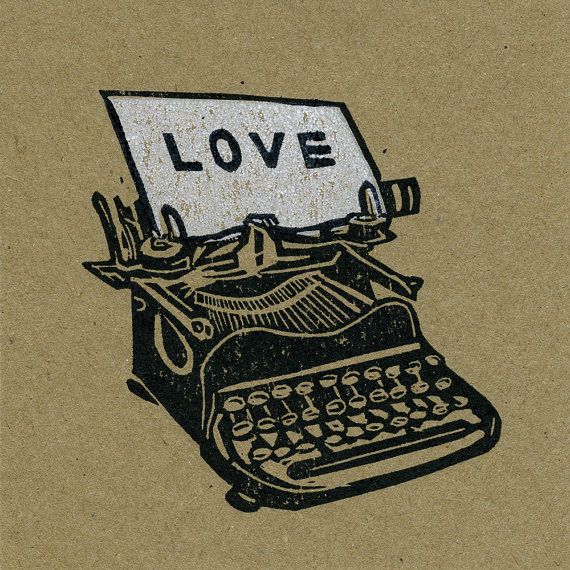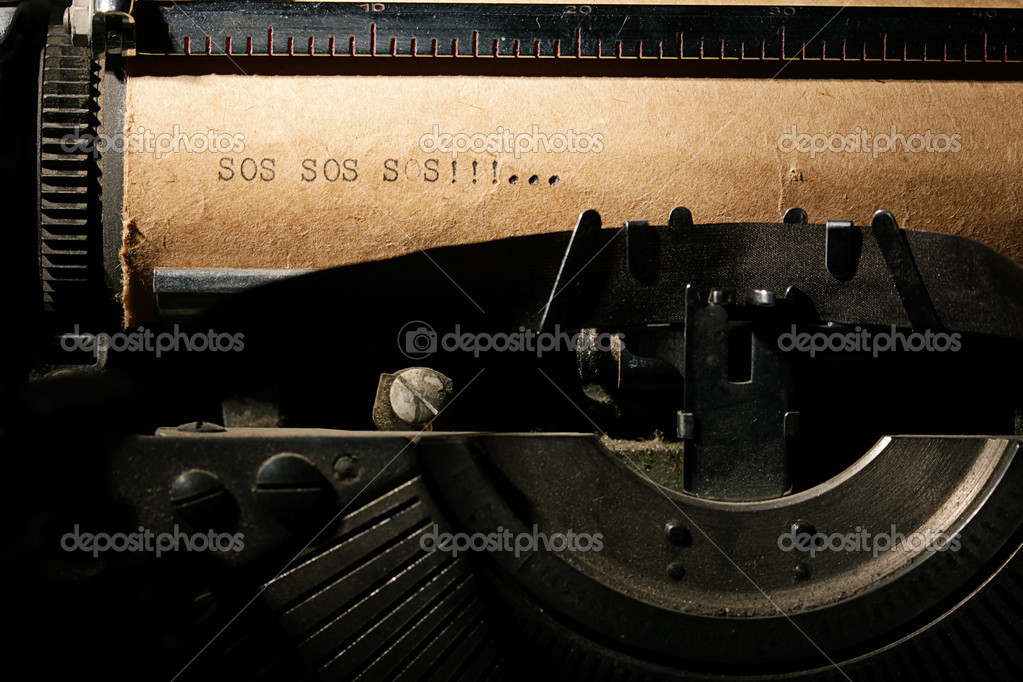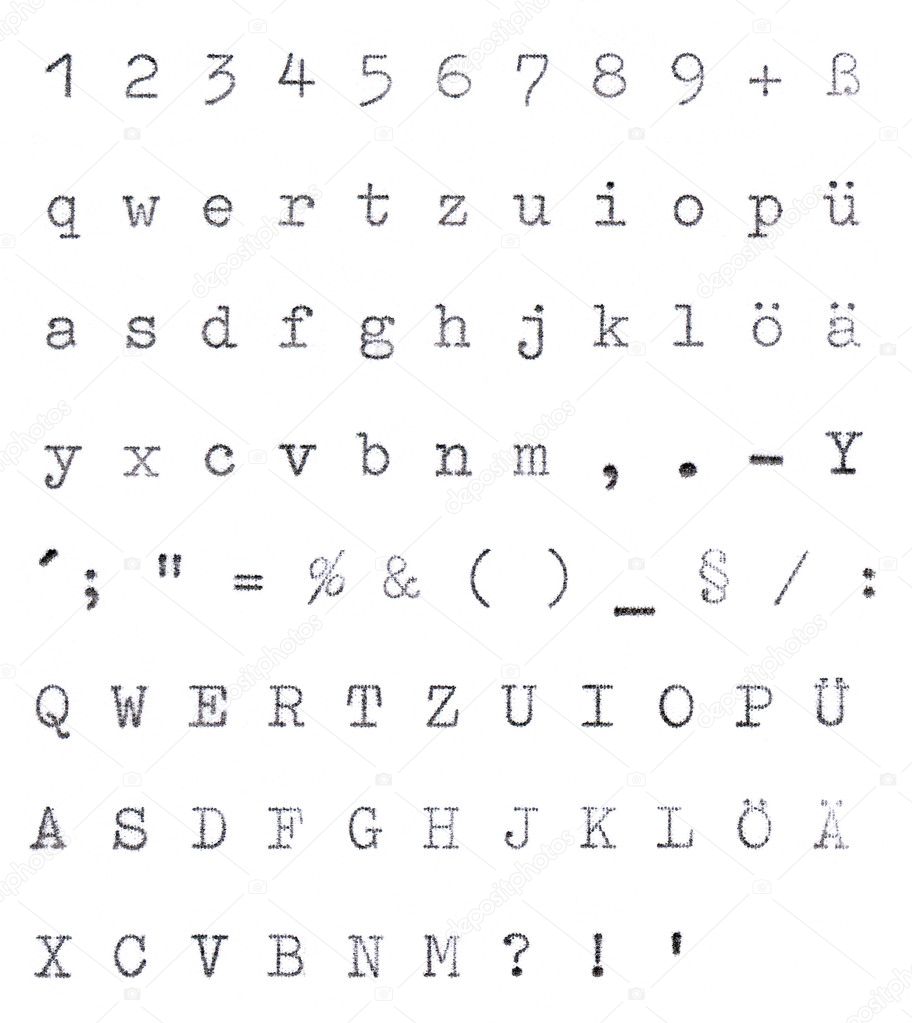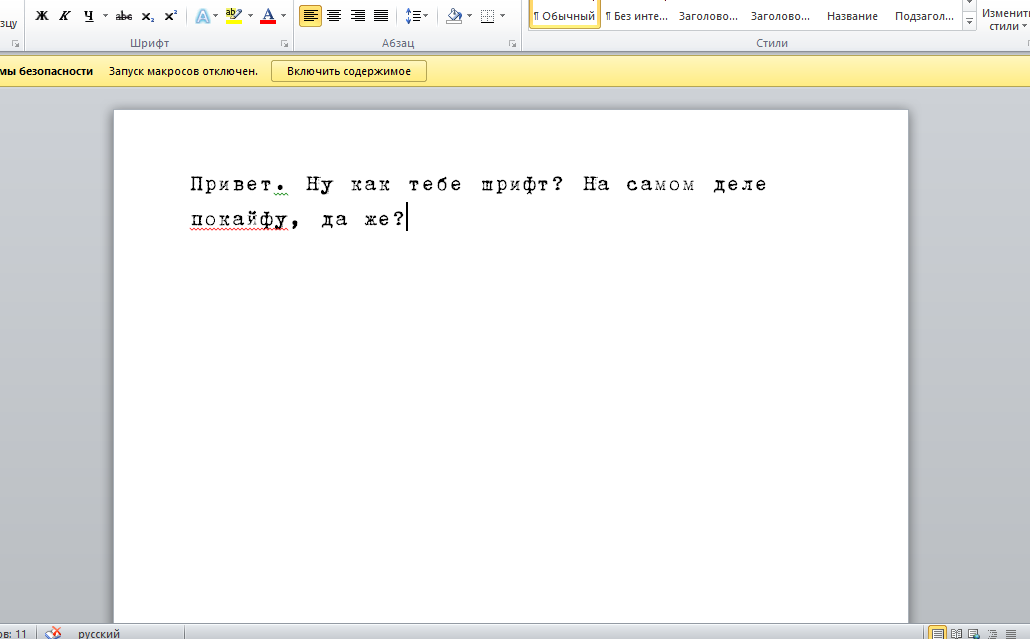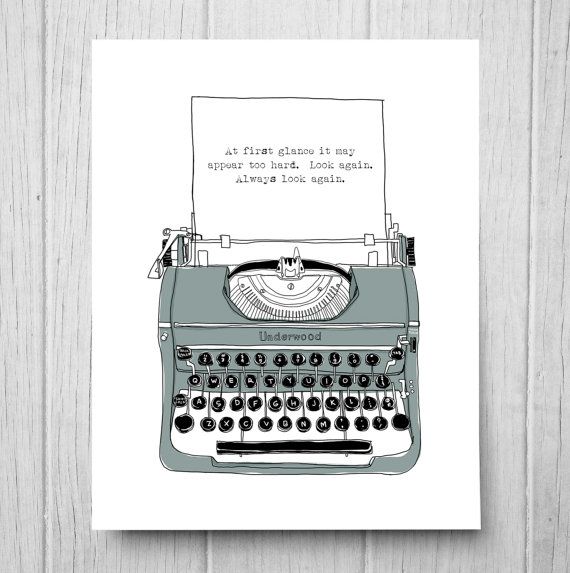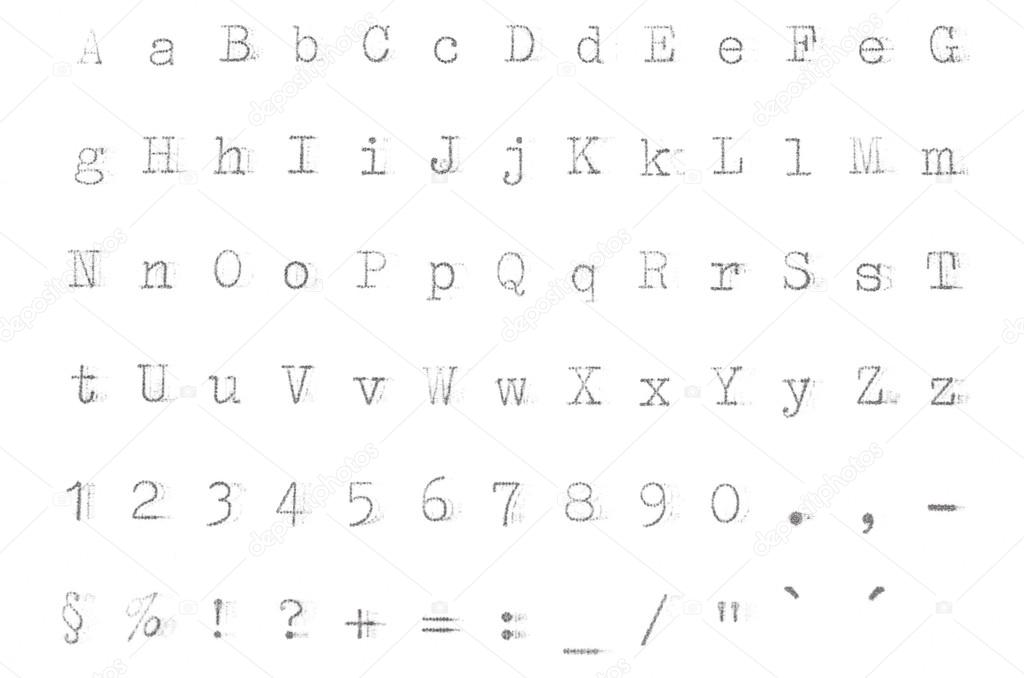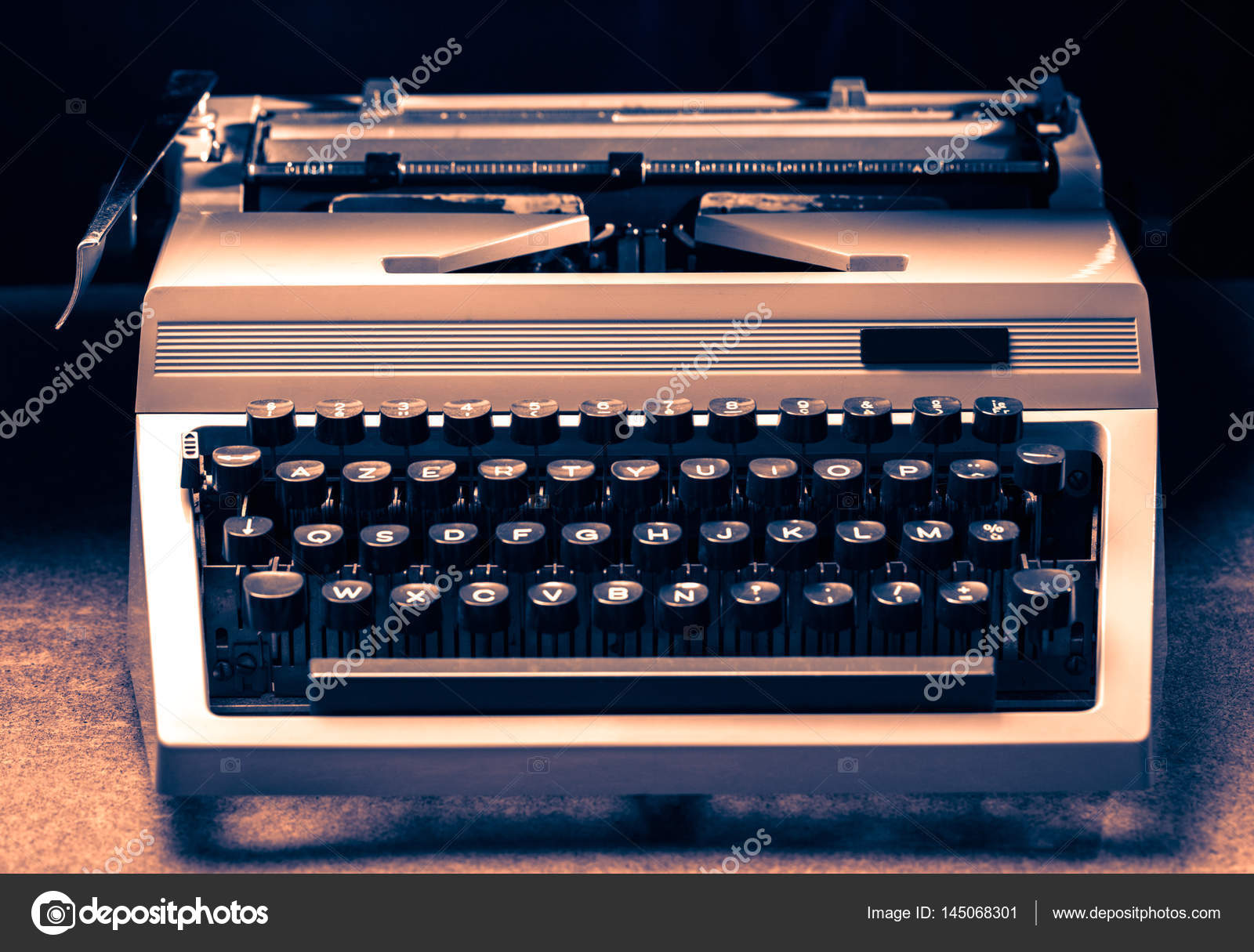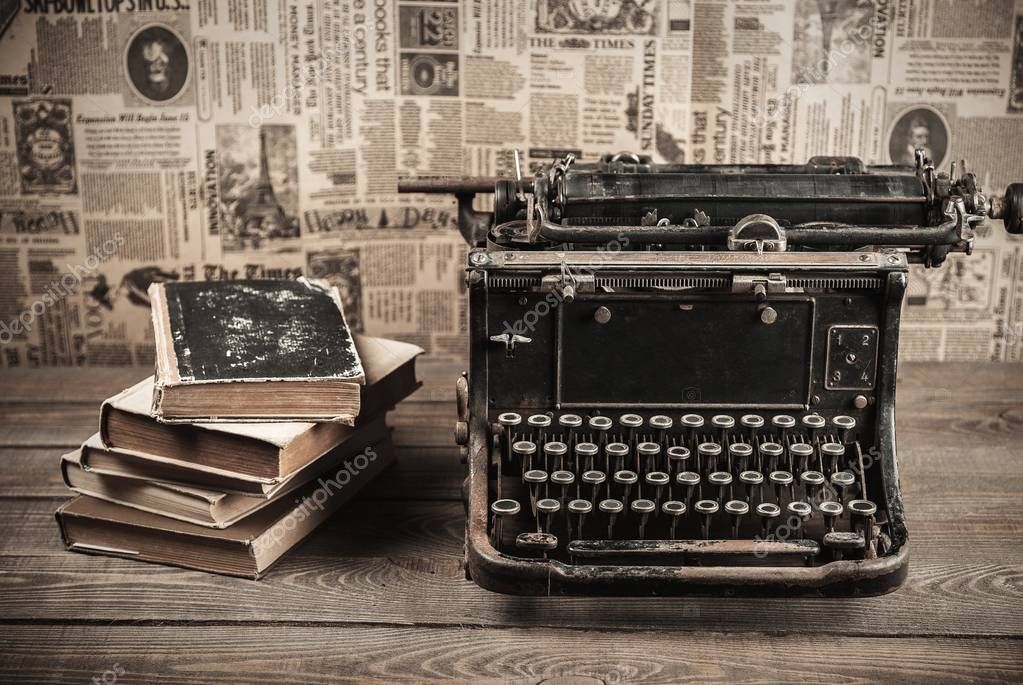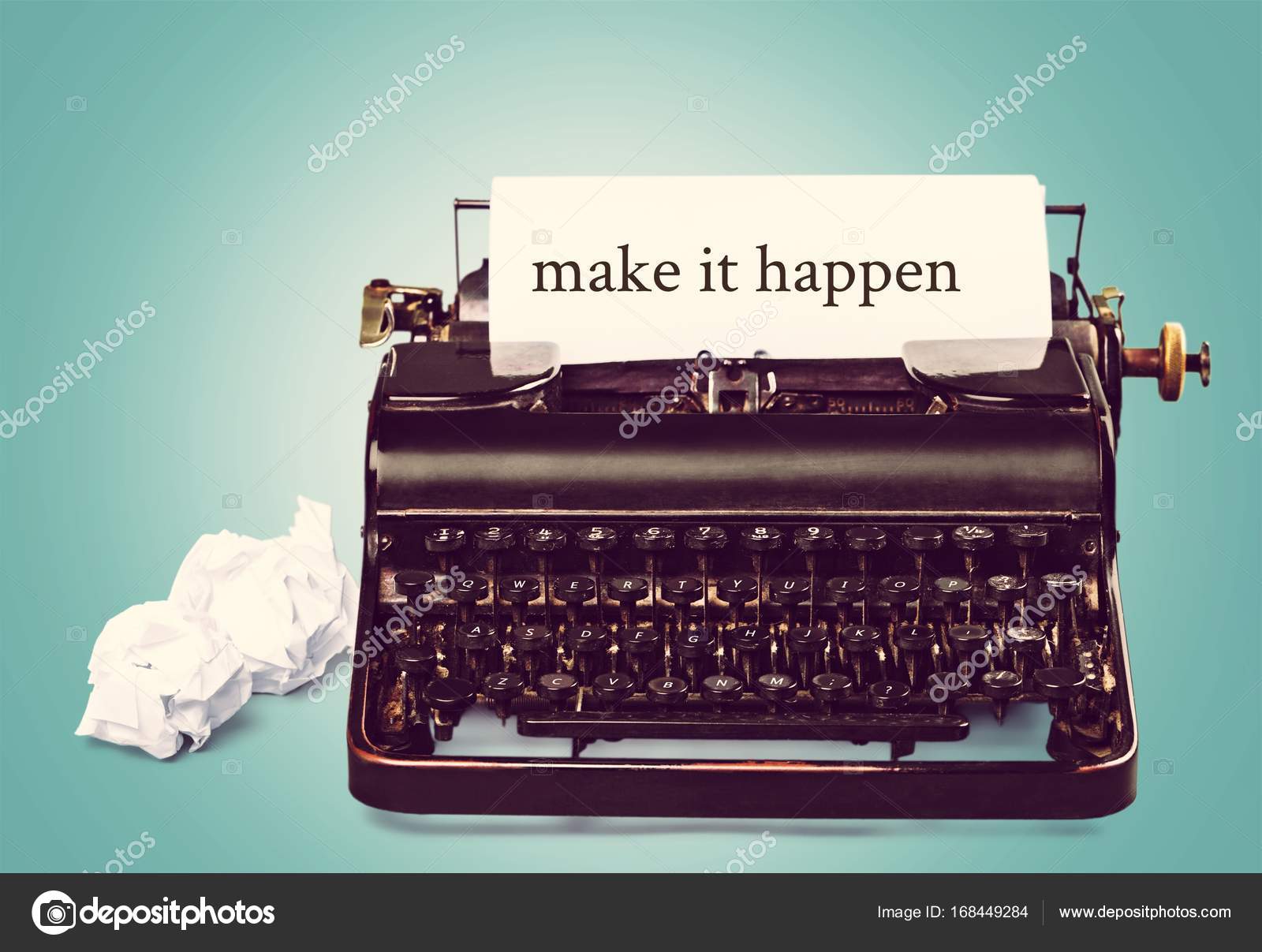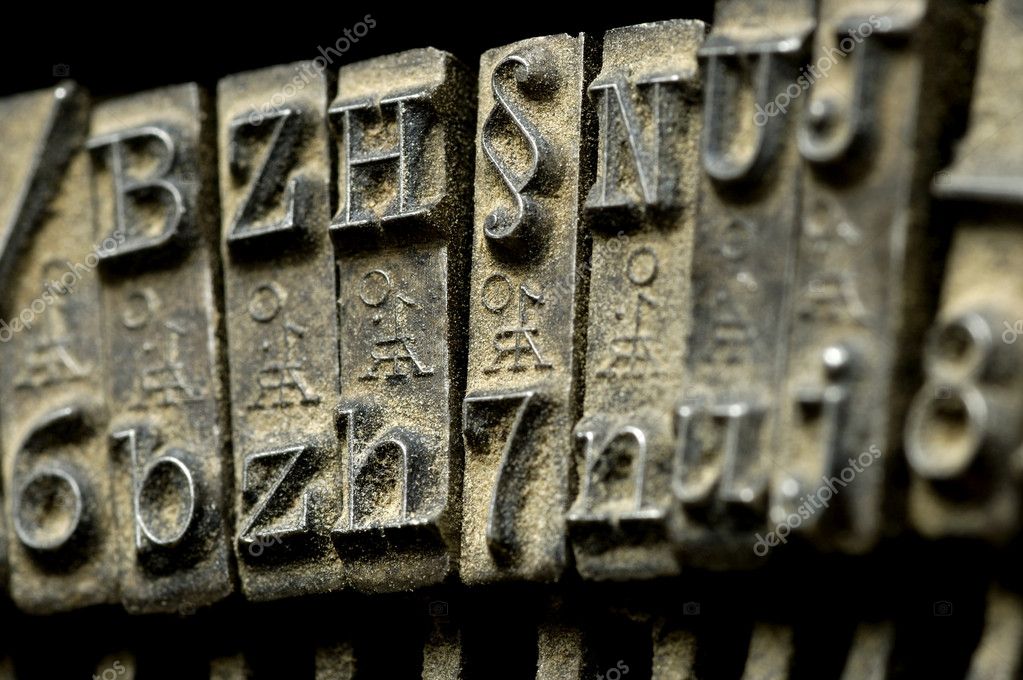
Пора сделать что-нибудь необычное, тебе не кажется? Настройте биографию профиля или выделите части подписей к фотографиям и видео, которые вы передаете. Преобразует обычный текст в разные стили Конвертер букв пишущей машинки, например шрифты для татуировок, каллиграфические шрифты, веб-скрипт, курсив, письменные источники от руки, различные символы, буквы, шрифты, символы и символы или красочные.
В различных социальных сетях используется шрифт, который лучше всего адаптируется к общему дизайну системы. Это часть точного единообразия визуального благополучия пользователей, просматривающих эти платформы.
✍ Конвертер букв пишущей машинки
Примеры, созданные с помощью генератора конвертера букв пишущей машинки
Unicode был изобретен для исправить проблему, вызванную большим количеством кодовых наборов. С самого начала программирования разработчики использовали свои языки, поэтому передача текста с одного компьютера на другой часто приводила к пустой трате информации.
Unicode пошел на многое в XNUMX-х, чтобы установить единичный набор символов охватывающий всю систему письма. Укажите единичное число для каждого символанезависимо от платформы, программы и языка.
El Стандарт Unicode может отображать шрифты и символы используется на любом языке; включая смайлы, которые также являются текстовыми символами.
Итак, с этим конвертером Конвертер букв пишущей машинки не создавать источники, но Символы Unicode что вы можете использовать в Instagram, Twitter, Pinterest, Fb, Tumblr, WhatsApp, TikTok
➕ Текстовые шрифты
Первый сто двадцать восемь символы из списка Unicode являются наиболее часто используемыми и известны как алфавит ASCII. Алфавит ASCII содержит буквы, десятичные цифры, знаки препинания и некоторые особые символы.
Тем не менее, ASCII не обращается к знакам с диакритическими знаками, вопросительным знакам или некоторым другим символам (математическим, греческие буквы,…) Это необходимо в разных контекстах.
Регулярность использования цифровых шрифтов противоречит этому — проблема, которую он заметил на якобы машинописных документах из фильмов «Джокер» и «Ирландец».
Его решение довольно техническое: если вам интересно, вы можете вникнуть в него здесь. Что еще более важно, TT2020 является бесплатным и открытым исходным кодом, может использоваться как в коммерческих, так и в личных проектах и поставляется в различных стилях и весах.
04. Rough Typewriter Font